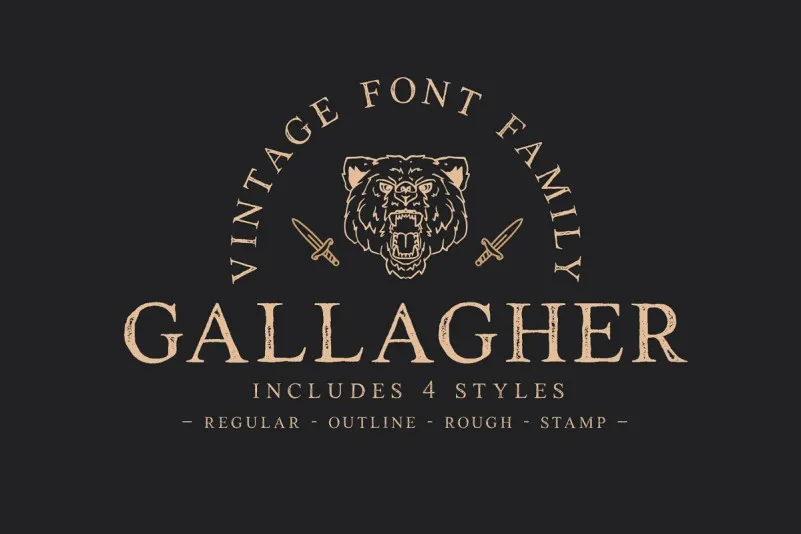
A fonte Gallagher é uma elegante serif que oferece um toque vintage para seu design. Criada pelo Surplus Type Co., ela combina arquitetura moderna com elementos retro, trazendo uma sensação de sofisticação e originalidade aos seus projetos. Suave e sofisticada, a fonte Gallagher é ideal para quando você deseja destacar sua marca em um produto. Suas aplicações vão desde previews e capas até logomarcas vintage e designs de camisetas. Esta font faz com que seu trabalho fique ainda mais único e atraente. Comprando Gallagher, você está adicionando uma pitada autêntica à sua paleta de recursos gráficos.